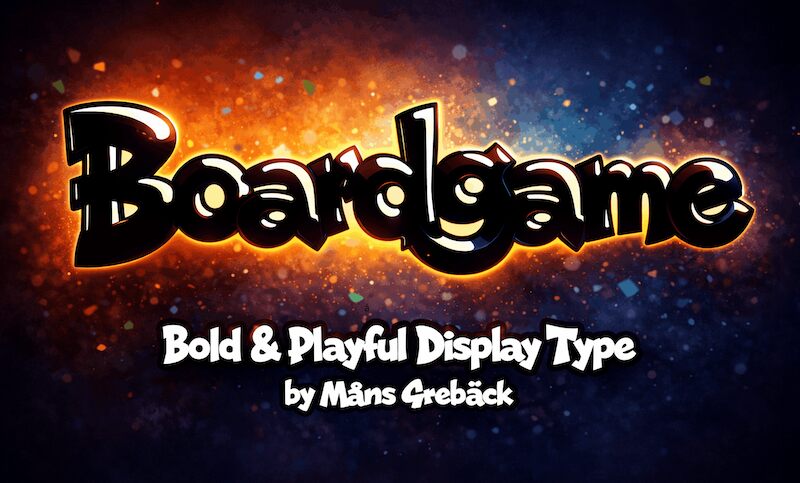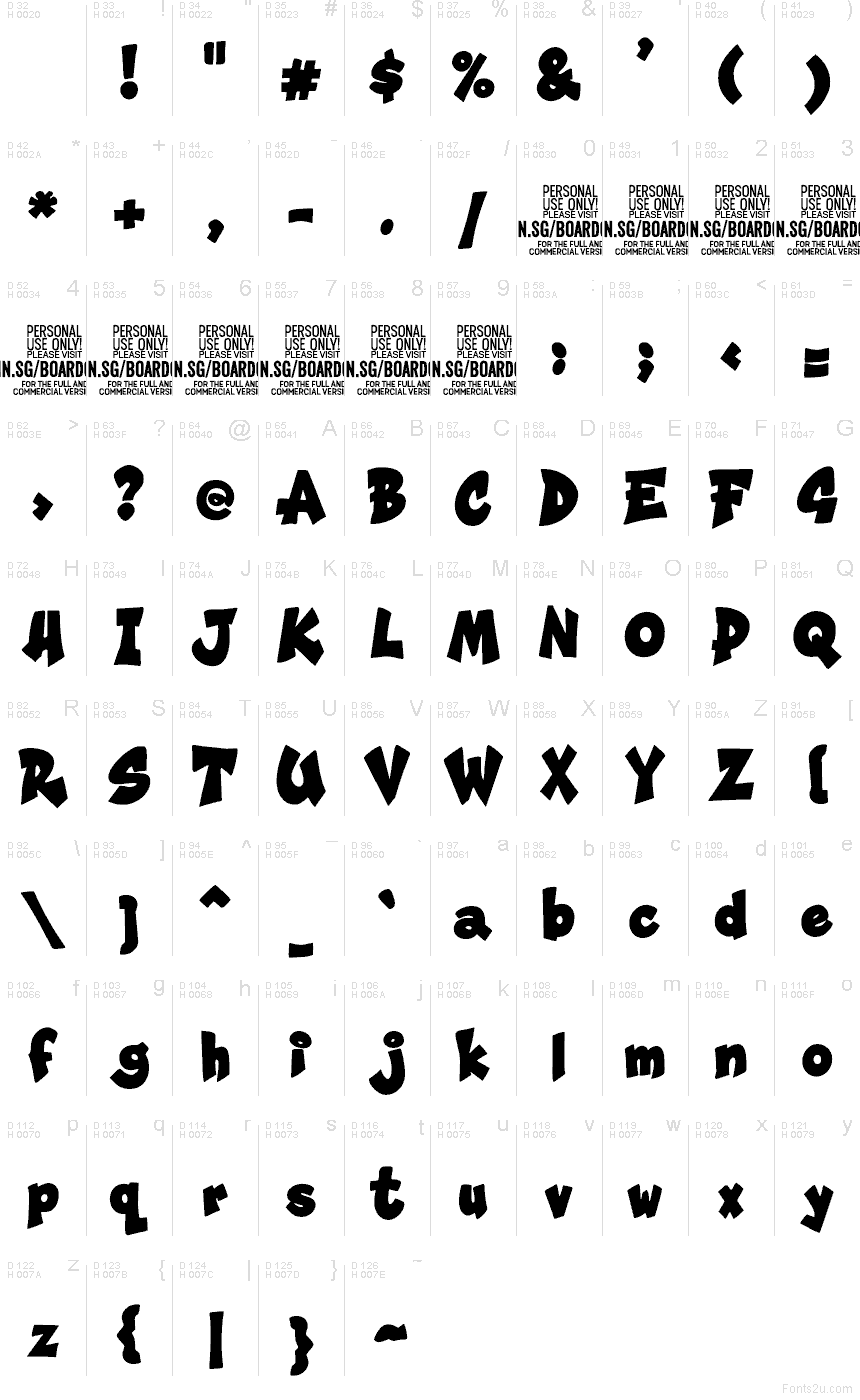
Boardgame Plain هو خط عرض مجاني مستوحى من أسلوب ألعاب الطاولة والقصص المصورة، يتميز بأشكال دائرية كبيرة وتصميم غير منتظم قليلاً يشبه قطع الورق المقوى المرحة. تحافظ الحروف على كتلة عريضة ومدمجة رغم حوافها المهتزة والمائلة، مما يضفي عليها طابع ألعاب الطاولة الحيوية بدلاً من مظهر القصص المصورة النمطي.
يُعد هذا الخط خياراً طبيعياً لعناوين صناديق الألعاب، ودعوات الحفلات، وملصقات الأطفال، وأوراق الأنشطة، وتغليف المنتجات المرحة حيث يساهم الخط الخارجي الديناميكي في إيصال الفكرة بسرعة. كما تستفيد العناوين القصيرة وشعارات الأسماء والصور المصغرة من هذا المظهر الضخم، خاصةً عندما تبحث عن طابع مرح وغير متكلف بدلاً من الشكل المنظم للغاية.